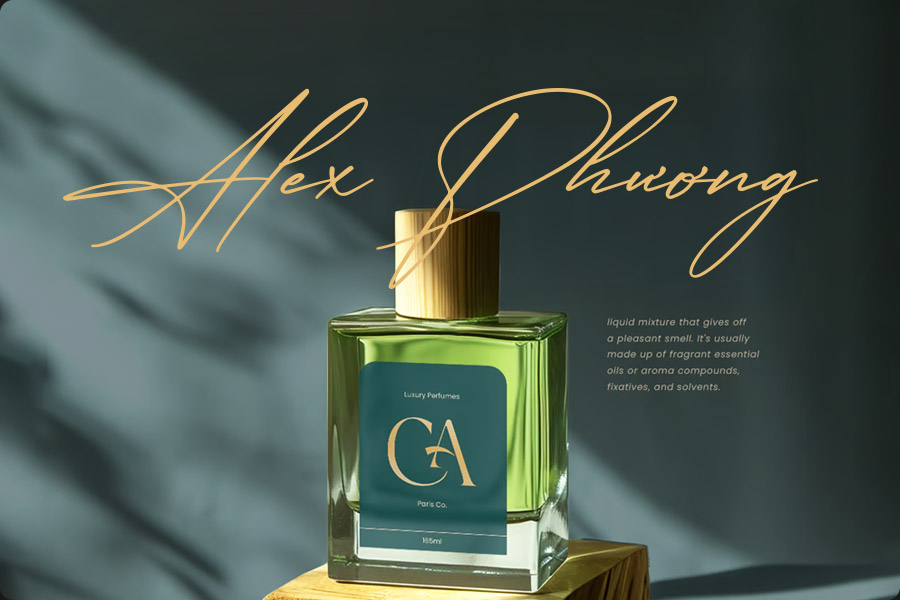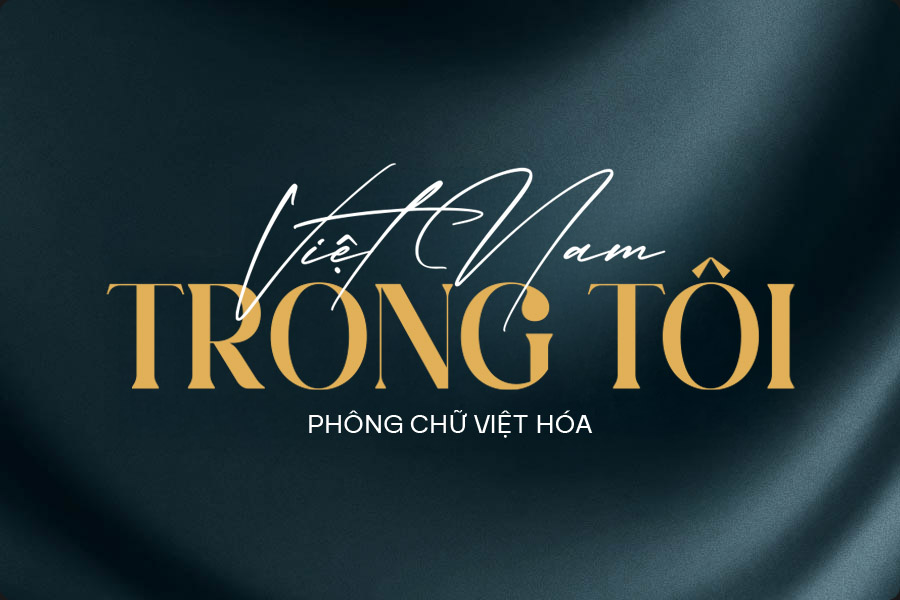
2 Font chữ Việt hóa phong cách serif cổ điển và chữ ký viết tay - Qalisha Signature
Qalisha Signature là bộ font gồm hai kiểu chữ khác nhau nhưng kết hợp với nhau rất ăn ý: một kiểu chữ có chân cổ điển, gọn gàng – và một kiểu viết tay chữ ký mềm mại, cá tính. Cả hai font đã được Việt hóa hoàn toàn bởi STYLEno.1 Fonts, hiển thị đẹp với tiếng Việt và dễ sử dụng trong mọi thiết kế.
Qalisha Signature – Font viết tay nghệ thuật, đầy cảm xúc cá nhân
Khác với vẻ chỉnh chu của font serif, Qalisha Signature lại mang vẻ nhẹ nhàng và cảm xúc hơn. Đây là kiểu chữ viết tay mềm mại, mô phỏng nét chữ ký, tạo cảm giác gần gũi và cá nhân. Rất thích hợp cho các thiết kế thiệp cưới, thư mời, tên thương hiệu cá nhân, chữ ký trên logo hoặc những câu trích dẫn nghệ thuật.
Qalisha Serif – Font chữ thanh lịch và sang trọng
Qalisha Serif là kiểu chữ có chân, nét thanh mảnh, rõ ràng, dễ đọc. Font mang lại cảm giác gọn gàng, tinh tế và sang trọng, rất hợp cho các thiết kế như logo thương hiệu, bao bì mỹ phẩm, poster thời trang, tiêu đề sách hoặc bìa tạp chí. Nó phù hợp với những ai cần font chữ vừa đẹp mắt vừa nghiêm túc.
Nguồn gốc và tác giả
Font Qalisha được thiết kế bởi Heru Utama Putra – một nhà thiết kế nổi tiếng đến từ Indonesia với nhiều bộ chữ đẹp và dễ dùng. Bản gốc phát hành bởi Letterena Studios, sau đó được STYLEno.1 Fonts Việt hóa, thêm đầy đủ dấu tiếng Việt để bạn sử dụng ngay mà không cần chỉnh sửa.
Dùng cả hai font trong một thiết kế giúp bạn tạo nên sự tương phản đẹp mắt: vừa trang trọng, vừa có cá tính riêng. Đây là bộ đôi hoàn hảo cho các dự án như wedding branding, thiết kế thiệp, logo thời trang, hoặc bài đăng mạng xã hội mang dấu ấn cá nhân.